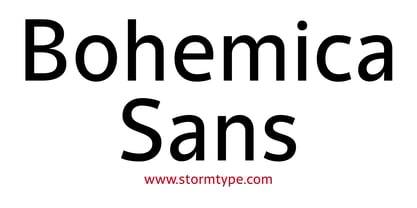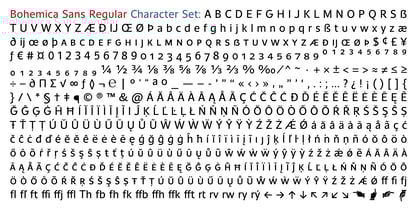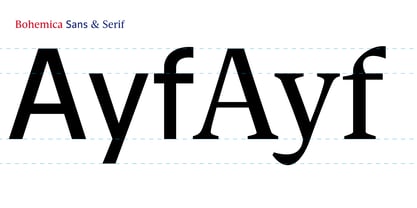
Bohemica Sans™
von Storm Type Foundry
Die Schriftfamilie Bohemica Sans wurde von František Štorm entworfen und von Storm Type Foundry veröffentlicht. Bohemica Sans enthält 1 Stile.
Bohemica is a legible text typeface created as part of a larger font system.
Designer: František Štorm
Herausgeber: Storm Type Foundry
Foundry: Storm Type Foundry
Eigentümer des Designs: Storm Type Foundry